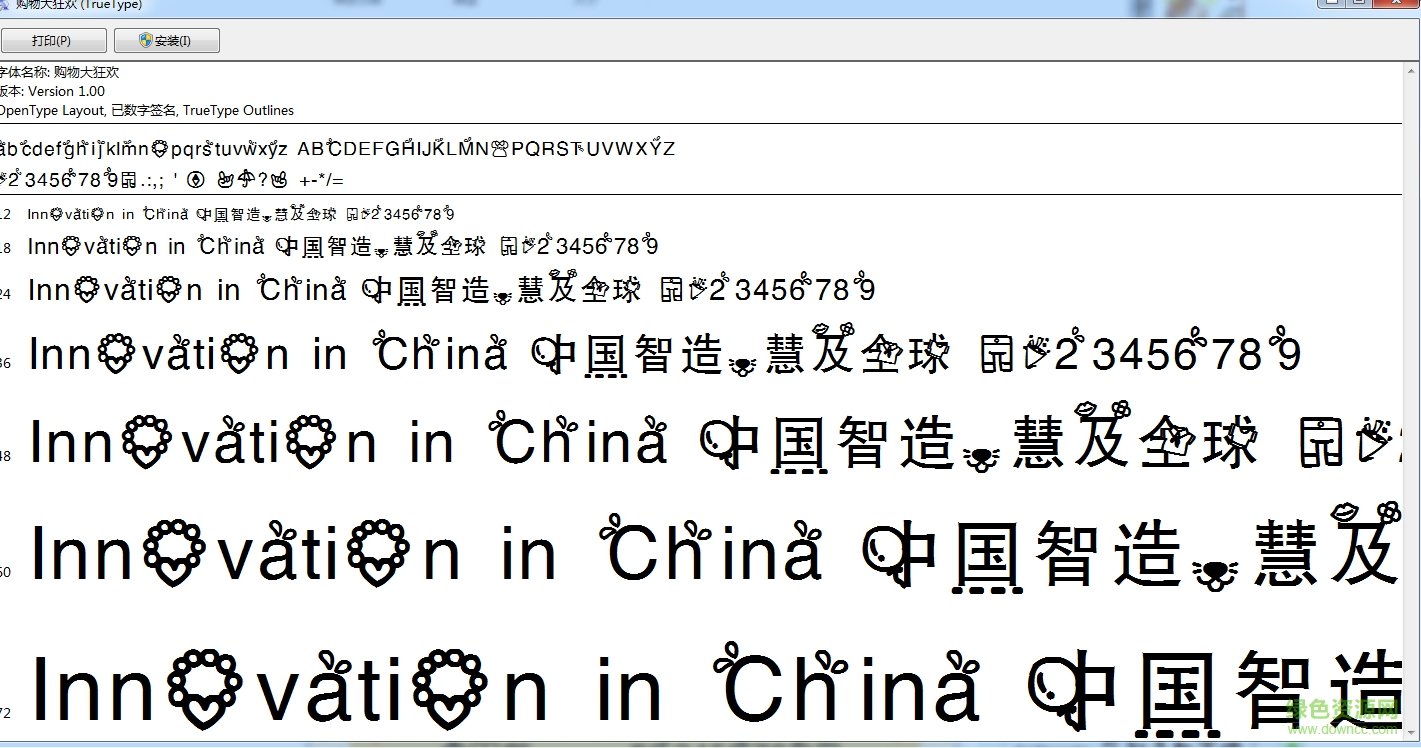
購物大狂歡中文版字體
購物大狂歡中文版字體是一款風格小清新的其他字體,濃濃的活潑有趣風格,節(jié)奏韻律感,色彩豐富明快,感興趣就趕緊來綠色資源網(wǎng)下載體驗!
購物大狂歡字體適用領(lǐng)域
購物大狂歡字體適用于兒童用品、運動休閑、時尚產(chǎn)品等主題,當然更適合網(wǎng)頁設(shè)計上使用了!